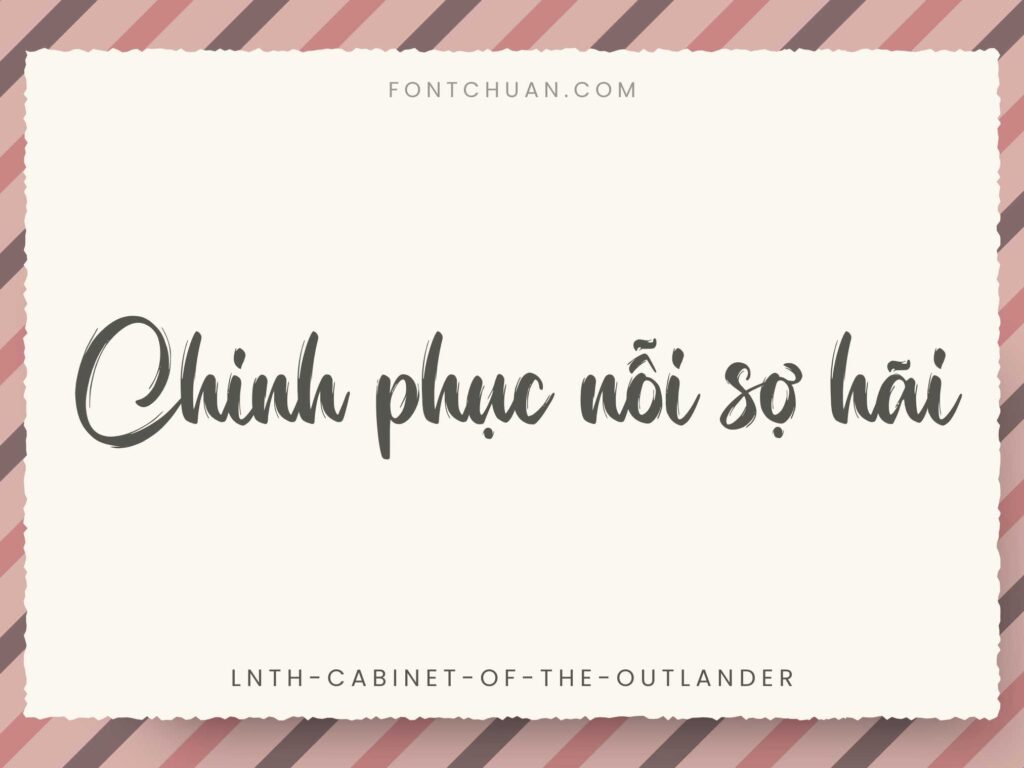
Font LNTH Cabinet Of The Outlander Việt Hóa
Cabinet of the Outlander là một phông chữ viết tay độc đáo, được thiết kế bởi Cat.B. Phông chữ này mang phong cách tự nhiên và phóng khoáng, với các đường nét mềm mại và uyển chuyển, tạo nên sự thân thiện và gần gũi cho các thiết kế. Phiên bản Việt hóa do LNTH thực hiện giúp phông chữ này hỗ trợ đầy đủ các ký tự tiếng Việt, giúp người dùng dễ dàng áp dụng trong các dự án đa ngôn ngữ. Phông chữ này đã được sưu tầm và đăng tải bởi thành viên của Font Chuẩn nhằm đáp ứng nhu cầu đa dạng của cộng đồng thiết kế.
Về đặc điểm thiết kế, Cabinet of the Outlander sở hữu các ký tự được thiết kế tỉ mỉ, mang lại cảm giác nhẹ nhàng và tự nhiên. Phông chữ này đặc biệt phù hợp cho các dự án như Font chữ ký, thiệp mời, bìa sách, poster, logo và các ấn phẩm quảng cáo, nơi cần sự tinh tế và ấn tượng mạnh mẽ. Ngoài ra, Cabinet of the Outlander cũng thích hợp cho các sự kiện như lễ hội, sinh nhật, Valentine và Trung thu, mang lại không khí ấm áp và lãng mạn. Trong lĩnh vực ngành nghề, phông chữ này được ứng dụng rộng rãi trong quảng cáo, thiết kế thiệp cưới, giáo dục và công nghệ, góp phần tạo nên sự độc đáo và thu hút cho các sản phẩm và thương hiệu.